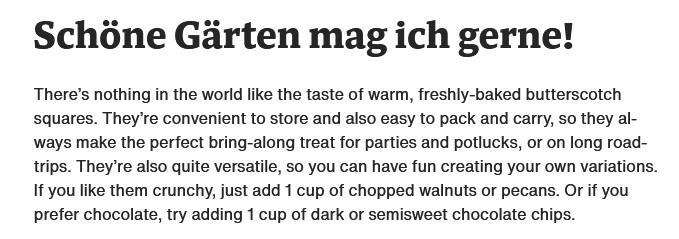
Mundo Serif pairing - Welche Font für Fließtext?
ich suche eine im Web gut lesbare Fließtext-Schrift in Kombination mit der Mundo Serif. Die Mundo Sans finde ich nur mäßig schön. Was haltet ihr von der Helvetica Now (siehe Anhang)? Habt ihr Ideen?
Was haltet ihr von der Helvetica Now
Wenn Du das Ganze umdrehst und die Helvetica zum Headline-Font machst und die Mundo Serif zur Fließtextschrift, vielleicht. Ansonsten würde ich Dir – zumindest bei großen Textmengen – eher davon abraten. Wenn überhaupt eine Sans für Fließtext, dann lieber eine humanistische, wie hier:
Aber dann kannst Du auch gleich bei der Mundo bleiben. Was also genau magst Du an der Mundo Sans nicht?
Ich würde die Tatsache, dass es hierfür einen idealen Gegenpart gibt (Sippe) ja eher als „Geschenk“ betrachten. ;-) Es sei denn Du brauchst Kontrast. Dann vielleicht besser eine warme Geometrische wie die Pluto Sans?
Ich finde die Mundo Serif einen Hauch zu dünn in Regular (Medium zu dick). Findest du die Mundo Serif allgemein für Headline nicht schön, oder jetzt nur in der Kombination?
Nee, ich finde die Helvetica mit ihren geschlossenen Formen für Fließtext eher ungeeignet. (Ich hatte mich glaube ich vertippt, vielleicht daher das Missverständnis.)
Danke. Vielleicht überlege ich mir das mit der Mundo Sans nochmal. Oder "langweilig" die Mundo Serif für beides? Hmmmm
Oder "langweilig" die Mundo Serif für beides?
Klar, kann man auch machen. Kommt auf das Projekt (insbesondere Layout und Zielgruppe) an, denke ich.
Ich finde die Mundo Serif einen Hauch zu dünn in Regular (Medium zu dick).
Gut, dass Du das im Blick hast. Das sollte gerade für Bildschirm-Anwendungen schon passen.
Bei der Serif fände ich den Regular-Schnitt eigentlich okay. Aber bei der Sans ist er für Web-Fließtexte ggf. tatsächlich etwas hell. Es gäbe aber auch noch einen Demi-Schnitt als Zwischenstufe zur Medium. Der dürfte funktionieren.
Oder Du nutzt die Sans für die Headlines. ;-)